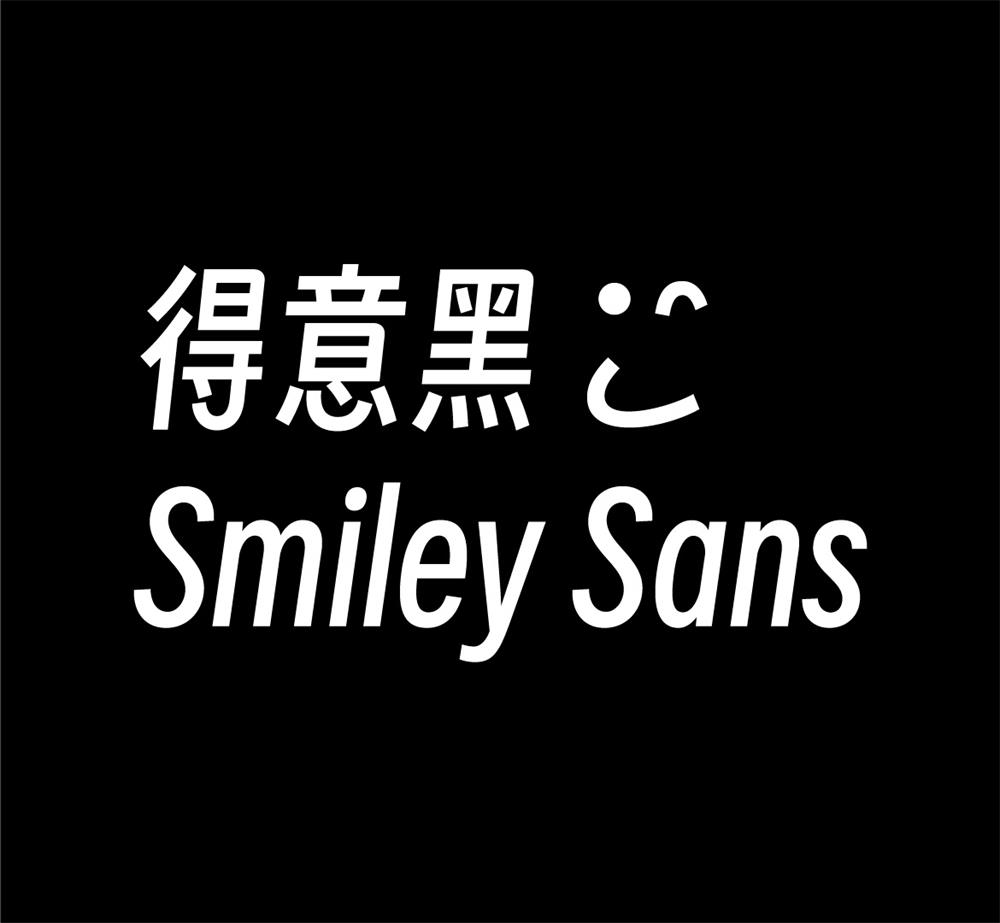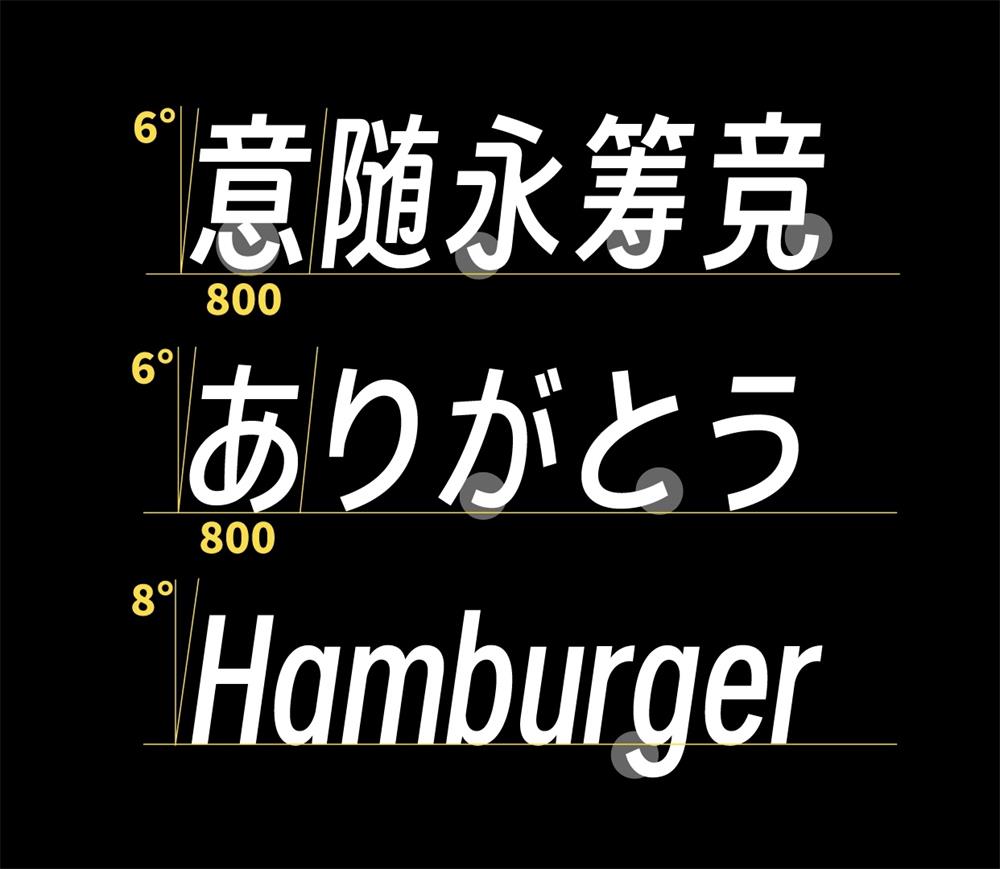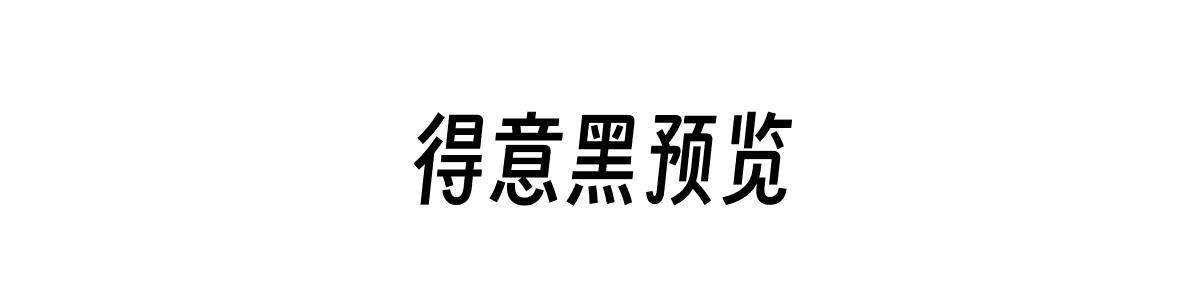
得意黑
得意黑(Smiley Sans)是一款在人文气质和几何感之间平衡得恰到好处的中文黑体。它没有走传统黑体那种方正呆板的路线,而是把字形做得偏窄,并带有一点自然的倾斜度,再加上不少借鉴手绘美术字的细节处理,整体既有复古味道,又很有现代潮流感。
在字库覆盖上,得意黑做得相当全面,不仅完整支持简体中文常用字,还包含了拉丁、西里尔、希腊字母以及日文假名、数字和标点,做多语言混排时整体视觉也很统一协调。
得意黑最有辨识度的地方,就是那一点点斜度和充满手绘感的细节。窄身加微斜让文字自带动感和轻快的节奏,而笔画里不规则的曲线变化,又去掉了机械字体的冰冷感,多了几分手写的温润灵动,把几何造型的理性和人文温度揉合在了一起。